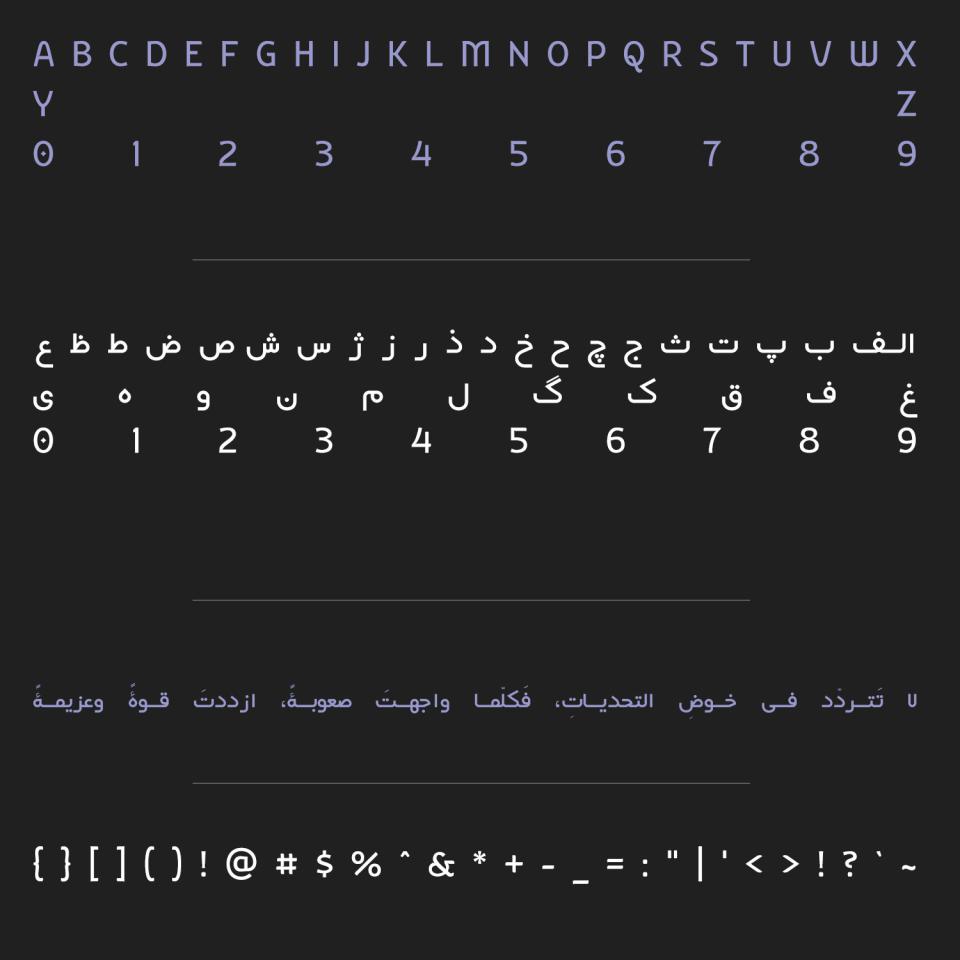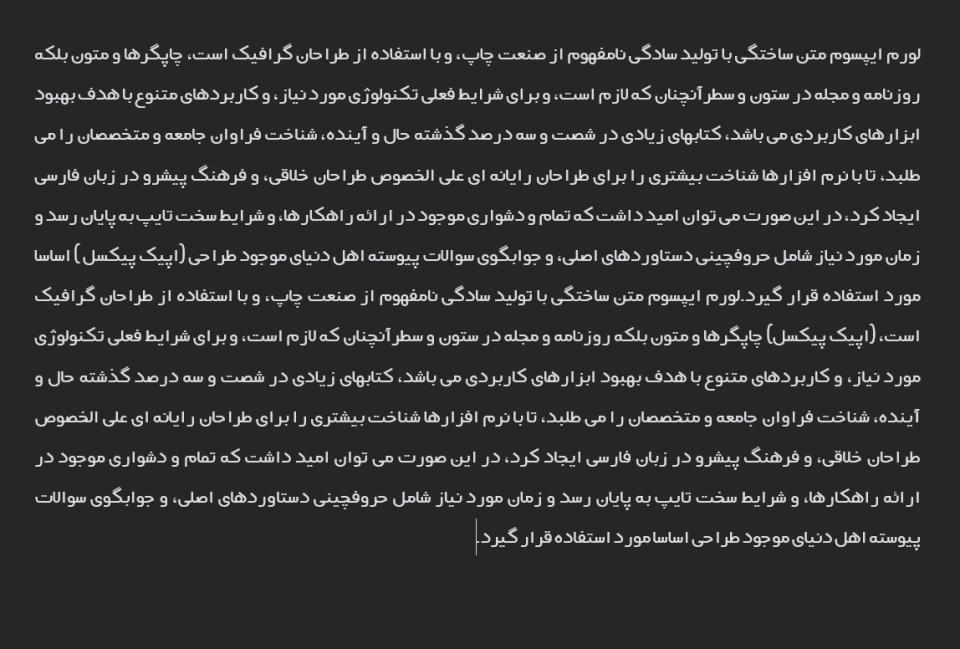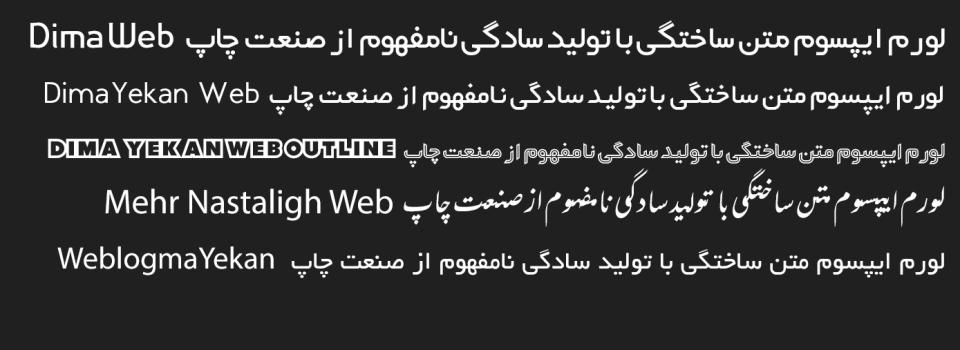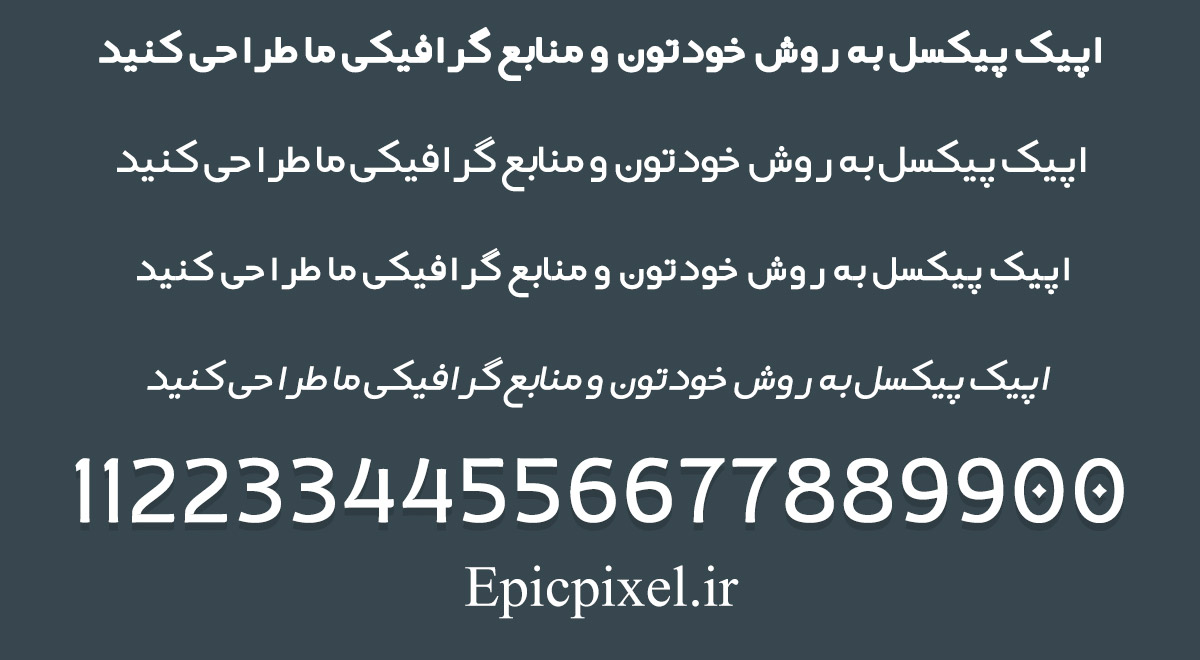
10 فونت وب فارسی Web
فونت دیما وب، یه انتخاب هوشمندانه برای کساییه که به دنبال یه فونت مدرن و کاربردی برای پروژه های آنلاینشون هستن. این فونت با طراحی ظریف و خوانا، هم برای متن های طولانی و هم برای عناوین جذاب، عالیه. یکی از ویژگی های برجسته ی دیما وب، هماهنگی بی نظیرش با انواع صفحه های نمایش و اندازه های مختلفه، یعنی خیالتون راحته که تو هر دستگاهی، سایت یا اپلیکیشنتون بی نقص دیده میشه.
دیما وب، علاوه بر ظاهر زیبا، به فکر کاربر هم بوده. فاصله گذاری مناسب بین حروف و کلمات، خستگی چشم رو کم می کنه و تجربه کاربری بهتری رو رقم می زنه. این فونت، تنوع زیادی هم در وزن ها و استایل ها داره، از خیلی نازک و ظریف گرفته تا خیلی ضخیم و پررنگ، که به شما اجازه میده به راحتی با هر نوع طراحی و سلیقه ای، هماهنگش کنید.
استفاده از فونت های وب فارسی، تجربه ی کاربری وب سایت شما را به طور چشمگیری بهبود می بخشد. فرض کنید وارد سایتی می شوید که نوشته هایش ناخوانا، نامرتب یا خسته کننده هستند؛ حس خوبی نخواهید داشت و احتمالاً سایت را ترک می کنید. فونت های وب فارسی با طراحی دقیق و حرفه ای، خوانایی متن را افزایش می دهند و به کاربران کمک می کنند مطالب را راحت تر و با لذت بیشتری مطالعه کنند. این موضوع به ویژه برای وب سایت هایی با محتوای طولانی مانند مقالات، وبلاگ ها و فروشگاه های آنلاین اهمیت زیادی دارد.
یکی از ویژگی های مهم فونت های وب فارسی، هماهنگی آن ها با زبان فارسی است. این فونت ها با در نظر گرفتن ساختار و ویژگی های خط فارسی، مانند اتصالات حروف و اعراب، طراحی شده اند و ظاهری زیبا و منسجم به متن می بخشند. این هماهنگی باعث می شود متن روان تر و طبیعی تر به نظر برسد و از ایجاد ناهماهنگی های بصری جلوگیری می کند.
دانلوددر نهایت، استفاده از فونت های وب فارسی حرفه ای، تأثیر مثبتی بر سئوی سایت شما نیز خواهد داشت. موتورهای جستجو به تجربه ی کاربری اهمیت زیادی می دهند و خوانایی و زیبایی متن از جمله عواملی هستند که در رتبه بندی سایت ها مؤثرند. با استفاده از این فونت ها، می توانید رضایت کاربران را افزایش داده و در نتیجه رتبه ی بهتری در نتایج جستجو کسب کنید. این فونت ها با نام “وب” نشان از تمرکز بر ارائه نوشتاری مرتب و مناسب برای محیط وب دارند.